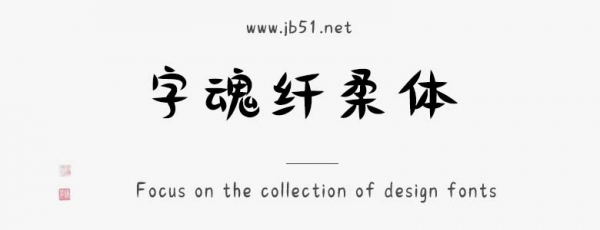
字魂纖柔體是由字魂字庫推出的,創(chuàng)意標(biāo)題字字體,該字體包含9503個(gè)中文、字母、 符號(hào)和數(shù)字,具有可愛活潑的風(fēng)格,適合應(yīng)用于藝術(shù)設(shè)計(jì)、平面宣傳設(shè)計(jì)、網(wǎng)頁設(shè)計(jì),書法字帖等領(lǐng)域。
字魂纖柔體字體是一款商用的創(chuàng)意,創(chuàng)意標(biāo)題字字體,該字體包含9503個(gè)中文、字母、 符號(hào)和數(shù)字,具有可愛活潑的風(fēng)格,可以滿足您設(shè)計(jì)上的各種需求,該字體主要用于包裝零售等場(chǎng)景, 您不但可以在字魂網(wǎng)下載字魂纖柔體字體,同時(shí)還有眾多毛筆書法字體、創(chuàng)意字體等可供選擇!